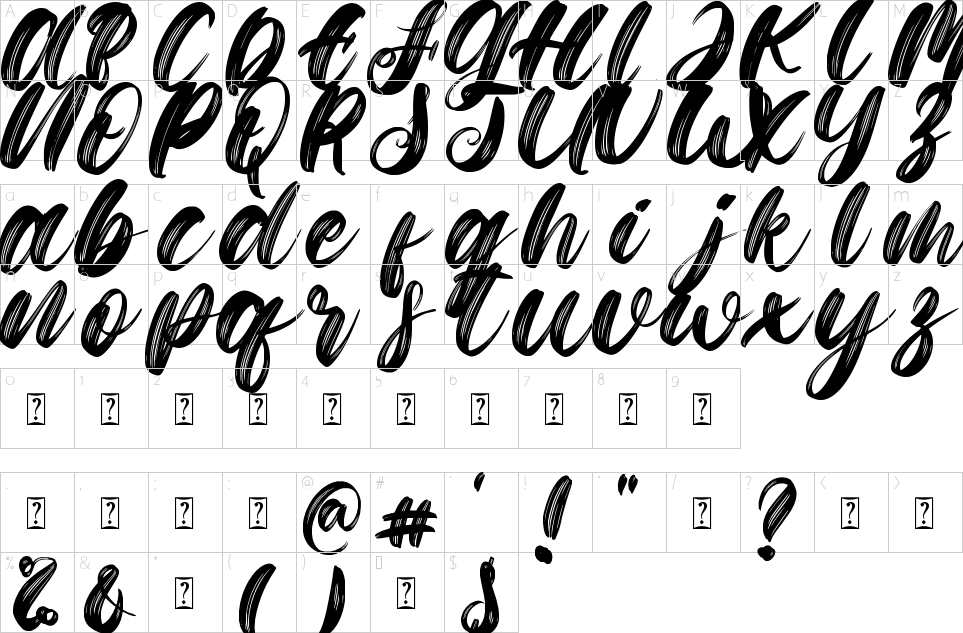
A Gloria Santa é uma elegante fonte que se destaca na categoria dos recursos gratuitos de fontes disponíveis para Windows e Mac. Desenhada pela Nox Studio, a font Gloria Santa foi criada com um equilíbrio perfeito entre modernidade e sofisticação, adequando-se perfeitamente tanto para aplicações profissionais quanto para projetos pessoais que valorizam uma autenticidade única. Com 2537 downloads desde sua disponibilização, é evidente que a Gloria Santa se tornou um dos recursos populares na categoria de fontes gratuitas. Suas linhas fluidas e delicadas garantem um texto legível em qualquer formato, fazendo-a ser particularmente adequada para textos longos ou gráficos exigentes. A sua facilidade de uso e versatilidade tornam-se uma opção confiável para qualquer designer que busca uma fonte elegante e única sem a necessidade de gastar dinheiro extra.